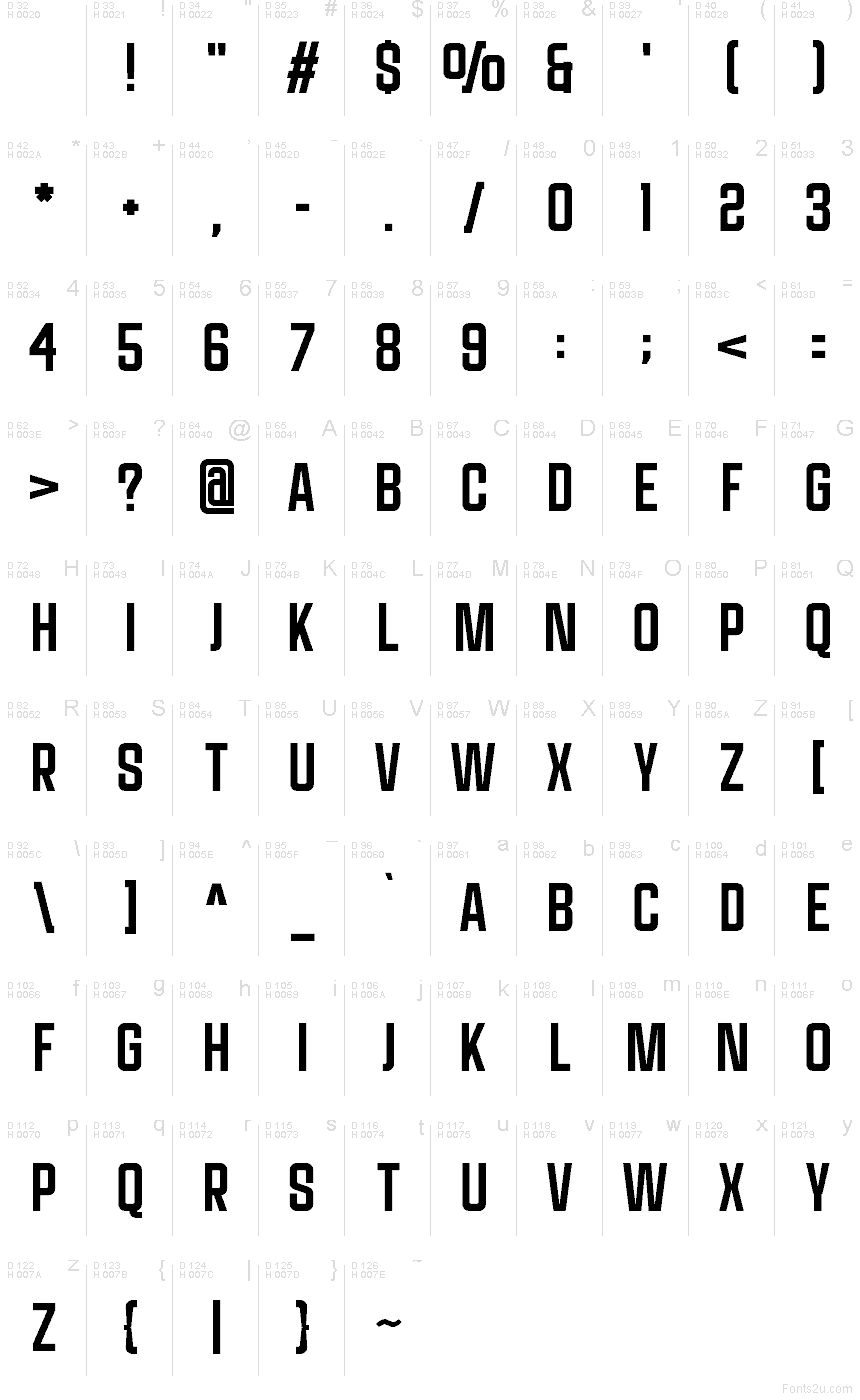
Muckley Blk par Ari Juanda est une police sans-serif condensée gratuite dotée de capitales imposantes et d'une structure affirmée aux allures d'affiche. De larges traits verticaux et des espaces intérieurs resserrés confèrent au lettrage une densité et une force marquées.
Les marques de streetwear et les salles de concert pourraient utiliser sa silhouette industrielle pour des logos, des affiches et des produits dérivés. En conception de magazines, ses formes étroites conviennent aux titres percutants et aux ouvertures de rubriques, en particulier pour les sujets liés à l'architecture urbaine, à la vie nocturne ou à la culture contemporaine.